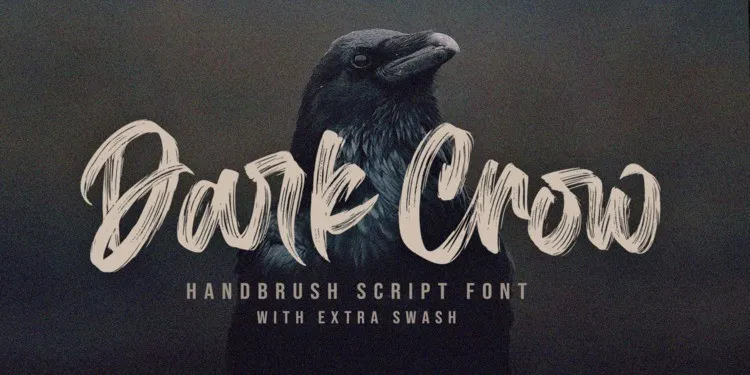
A Dark Crow Brush Font é uma escolha perfeita para qualquer projeto onde você precisa de uma script moderna com textura linhas. Essa fonte brush foi projetada por Mans Greback e compartilhada através do site 99designs. Com seu design cuidadosamente elaborado em 2020, essa fonte tem um realismo extraordinário graças às múltiplas ligaturas que criam uma aparência incrivelmente autêntica e natural. Ideal para seus projetos de design, eventos e muito mais, esta brush script é perfeitamente adaptada para quando você precisa criar letras com um toque de sofisticação. Seja em logotipos, materiais impressos ou até mesmo em criações digitais, a Dark Crow Brush Font traz uma mistura única de estilo e sofisticação. Essa fonte é especialmente perfeita para aqueles que buscam uma aparição moderna e autêntica no design de sua marca ou projeto, sem perder o charme das letras grafadas à mão. Além disso, a Dark Crow Brush Font pode ser usada em diversos formatos, seja ela aplicada sobre fundo sóbrio ou iluminado. Ela está equipada com várias ligaturas que ajudam a criar textura natural e um acabamento de letra perfeito, dando ao seu design uma aparência mais realista e profissional. A fonte está disponível para ser usada tanto em desktop quanto na web, tornando-a acessível e versátil para qualquer designer gráfico ou artista digital.